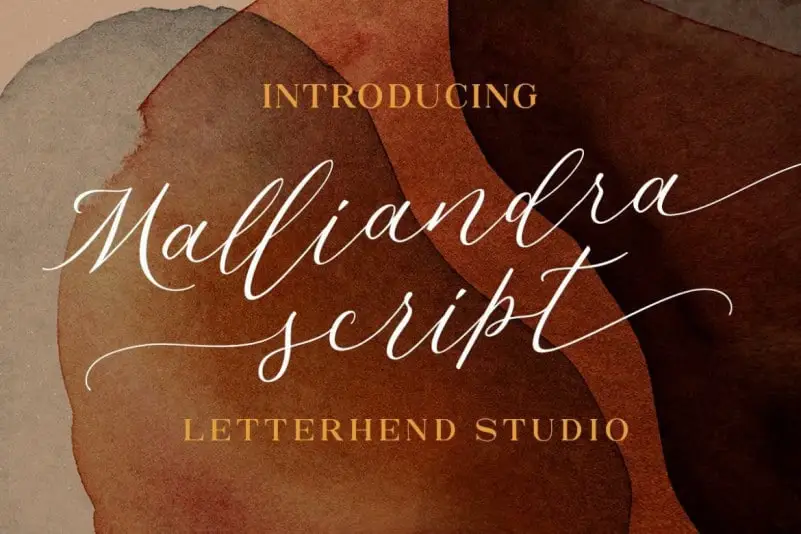
Malliandra Calligraphy Font – Download Grátis
Malliandra Calligraphy Font é uma fonte de caligrafia que traz uma sensação única, delicada e imersiva, inspirando criatividade por meio do seu estilo elegante e romântico. Desenvolvida pelo Designer Hamilton para o studio Letterhend Studio, esta fonte se torna um complemento perfeito para qualquer projeto de design gráfico que busque expressar detalhes sutis e a harmonia da caligrafia tradicional. Floridamente elegante, Malliandra Calligraphy Font não apenas adicionará uma nuance única ao seu trabalho em caligrafia, mas também oferecerá inúmeras possibilidades para personalizar e aprimorar sua obra de arte. Possui PUA (Private Use Area) que facilita o acesso aos seus caracteres especiais e suas suaves alternativas. Com esses recursos, você pode criar designs mais expressivos e variados, tornando-os ainda mais únicos. Com Malliandra Calligraphy Font na sua carteira de ferramentas gráficas, não há limites para a originalidade e criatividade que você pode alcançar em seus projetos. Seja uma carta personalizada, um banner editorial ou até mesmo um design digitalmente gerado, Malliandra estará lá para dar seu projeto aquele toque especial.